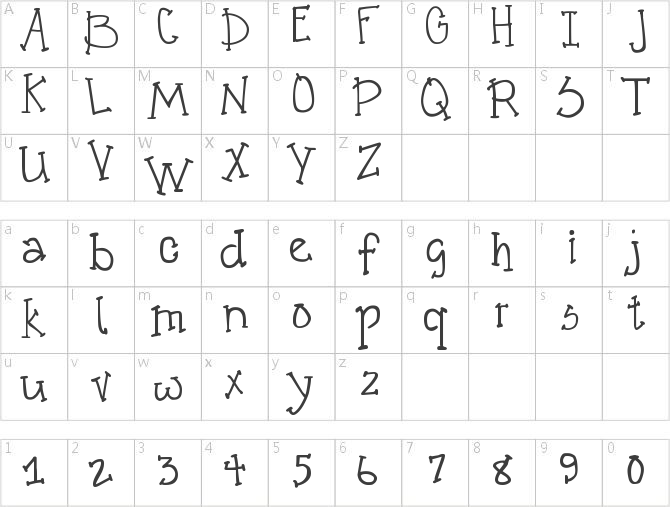
DJB Crazy Goofy Cool 詳情頁
字體名稱: DJB Cra
DJB Crazy Goofy Cool
DJB Crazy Goofy Cool介紹
DJB Crazy Goofy Cool字體字庫是一款讓人賞心悅目、百看不厭的英文字體,適合各類廣告和產品包裝設計應用,字體大小0.02MB,格式為ttf字體,上傳用戶是/zyj【GF】,作者/版權方為未知